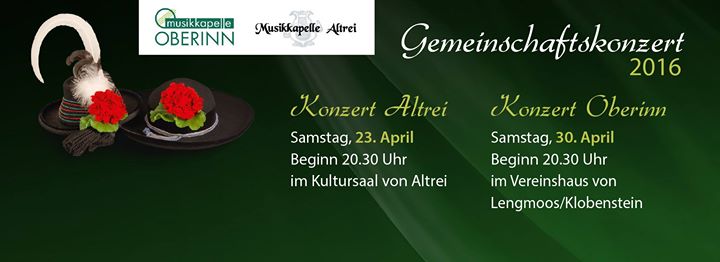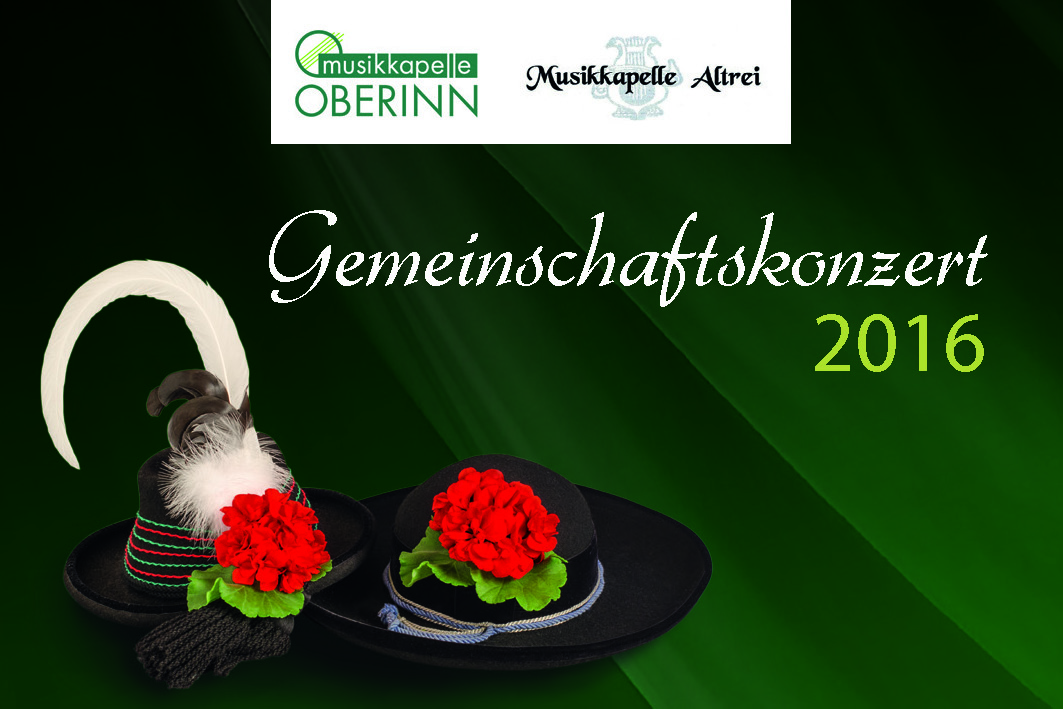
wie heißt diese Schrift?
Kann mir wer weiterhelfen, ich würde dringend diese Schrift benötigen (Bild im Anhang).
Die Schrift mit den Worten "Musikkapelle Altre" meine ich.
Wo bekomme ich diese Schrift her?
Vielleicht kann mir netterwese wer weiterhelfen,
Google wirft mir da einige Bilder vor die Füße. *AUA* Genau auf den kleinen Zehen ...
Für den Namen wird wohl eine „Black Chancery“ verwendet?
Aber der eigentliche Text wird in einer anderen Schrift geschrieben ... die ich kenne aber gerade nicht finde. Denkblockade ... *knirsch*
Vielleicht kann da einer der anderen ForistInnen aushelfen?
Das dürfte wohl die Gabrielle sein. Die Schrift, welche ursprünglich Gabriele heißt erschien lt. GlobalType-Datenbank 1938 bei der Schriftgießerei Wilhelm Woellmer und wurde von Hans Möhring erstellt. Dieter Steffmann hat sie dann digitalisiert.